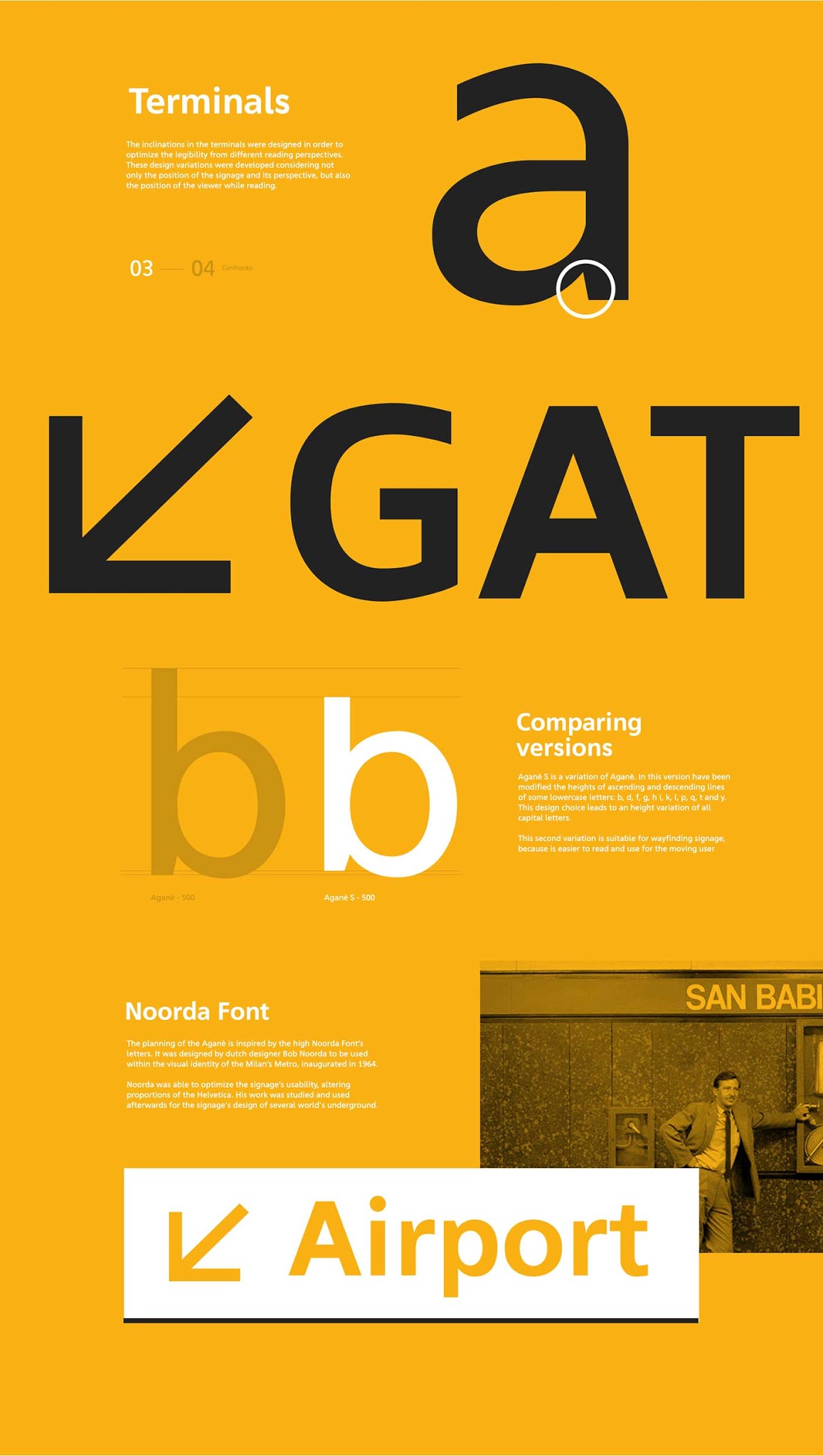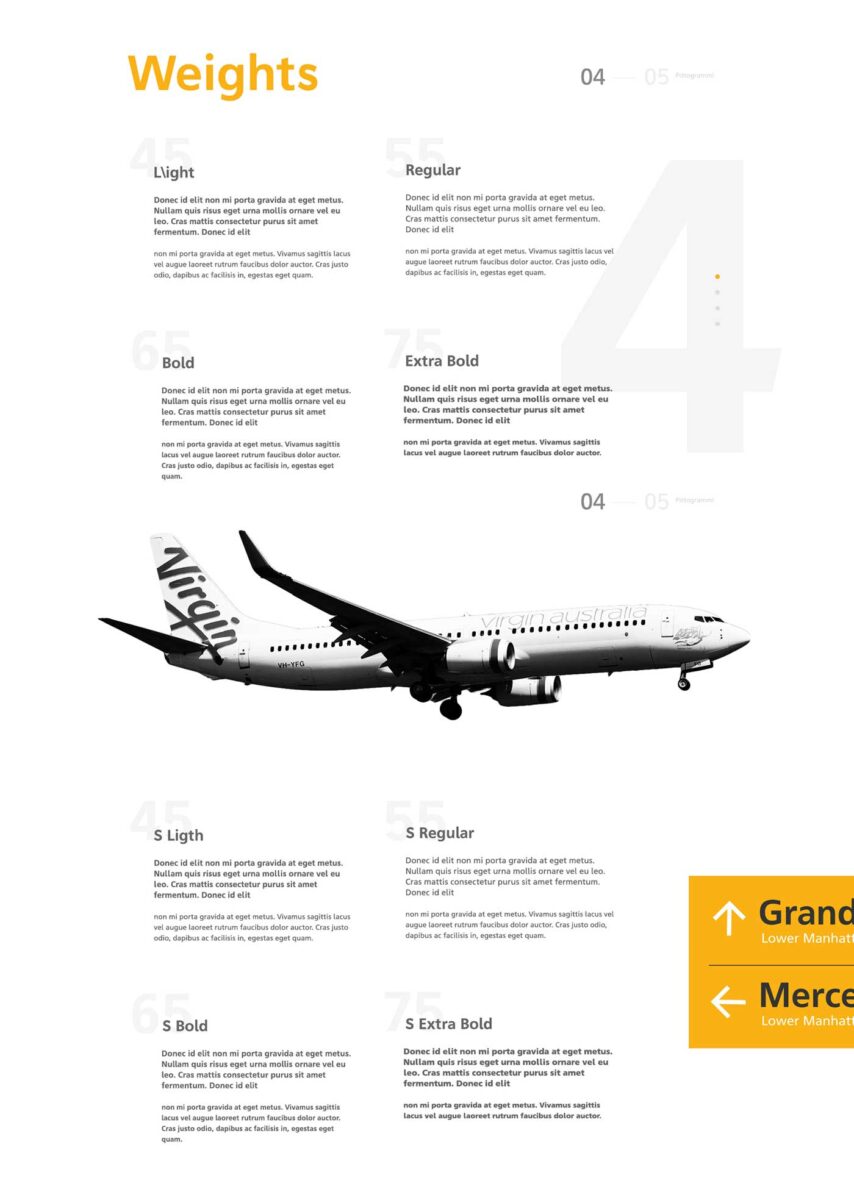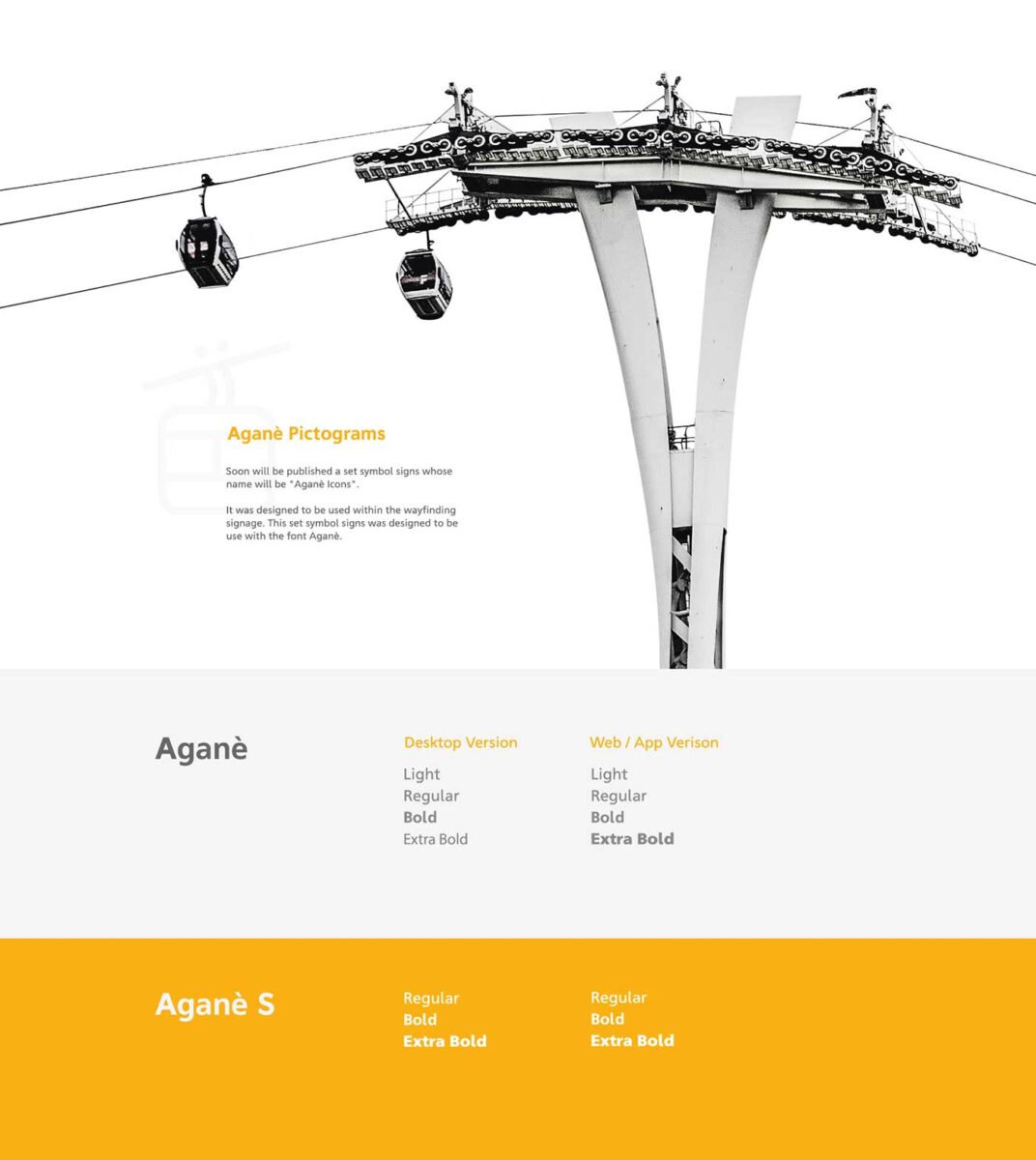
Aganè Free Font menawarkan estetika modern dan elegan yang cocok untuk berbagai keperluan, mulai dari desain website dan logo hingga dokumen resmi dan presentasi. Font sans-serif ini memiliki bentuk huruf yang simpel namun tetap menawan, dengan detail subtil yang memberikan kesan sophisticated.
designer | Danilo De Marco a Type designer, Web & Graphic designer from Switzerland |
Pilihan Tipografi Modern dan Elegan untuk Proyek Anda
Kelebihan lain adalah ketersediaan dalam berbagai gaya (regular, bold, italic, dan bold italic), memungkinkan Anda untuk bereksperimen dan menemukan kombinasi yang sesuai dengan kebutuhan desain.
Aganè typeface tersedia dalam 4 jenis karakter huruf, yaitu light, regular, bold dan extra bold.
Jenis Huruf ini menjadi pilihan tepat bagi siapa saja yang mencari font berkualitas tinggi tanpa biaya. Dengan desainnya yang modern dan fleksibilitas lisensi, Aganè Free Font dapat membantu Anda menciptakan proyek desain yang profesional dan memukau.